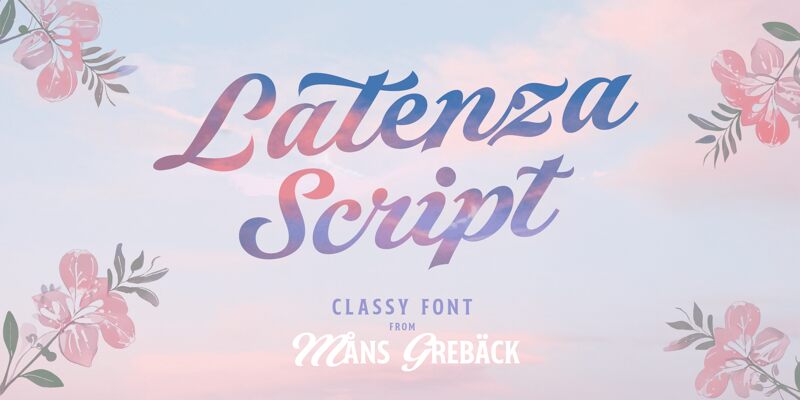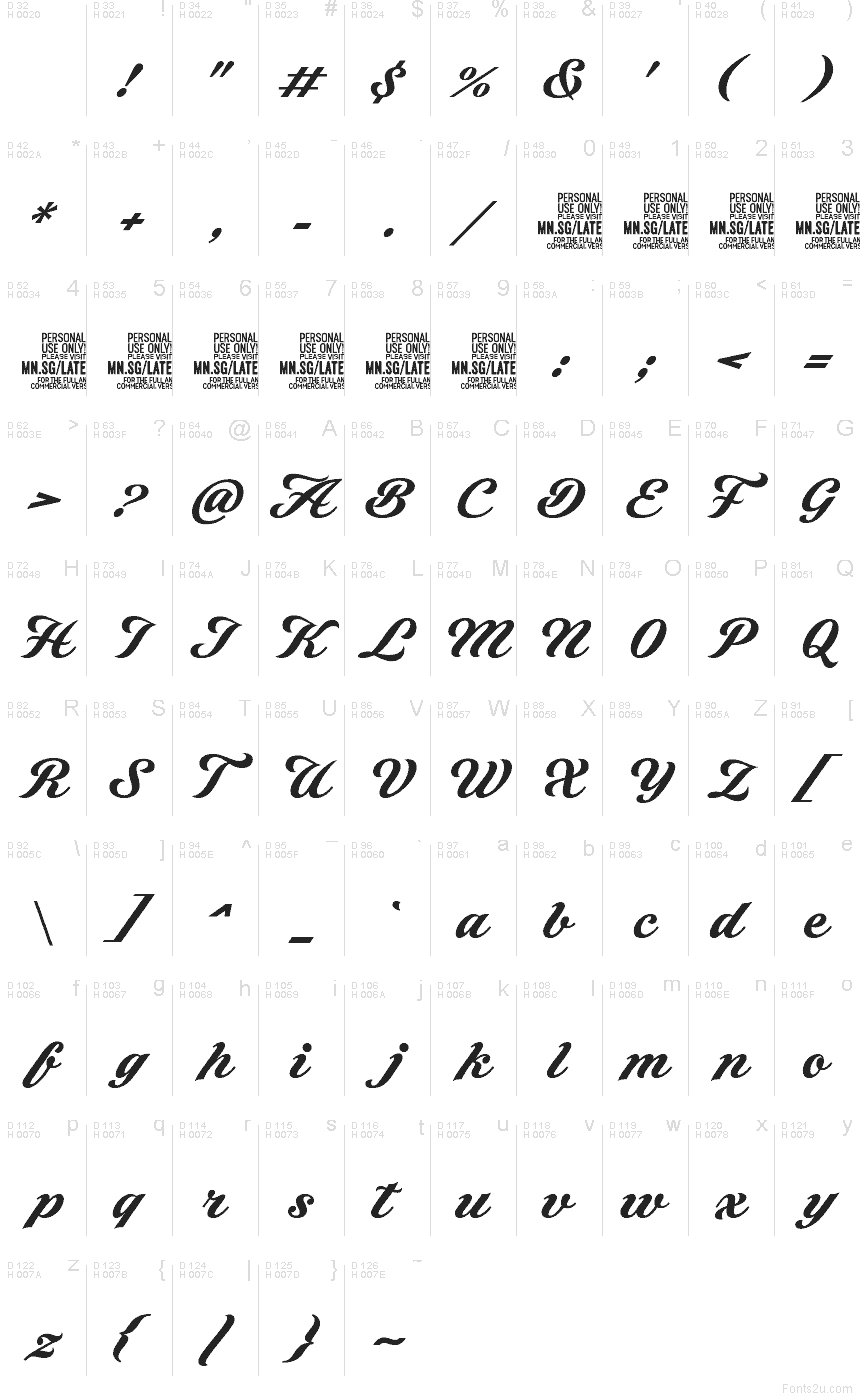
Latenza Script PERSONAL USE Regular
Latenza Script, de Mans Greback AB, es una tipografía caligráfica gratuita con el estilo y la fluidez de las letras de rotulista profesional. Las letras se inclinan hacia adelante en un movimiento continuo, combinando curvas amplias y brillantes con trazos de entrada y salida definidos, lo que confiere a toda la fuente un aire elegante y a la vez dinámico.
Es ideal para packaging de belleza, logotipos de boutiques, papelería de bodas, portadas de revistas y branding de cafeterías, especialmente donde una palabra corta o un nombre permite que esos largos trazos iniciales y finales respiren. Como fuente gratuita, también es perfecta para citas en redes sociales y tarjetas de presentación, donde su ritmo fluido aporta un tono elegante y manuscrito incluso a las líneas más cortas.